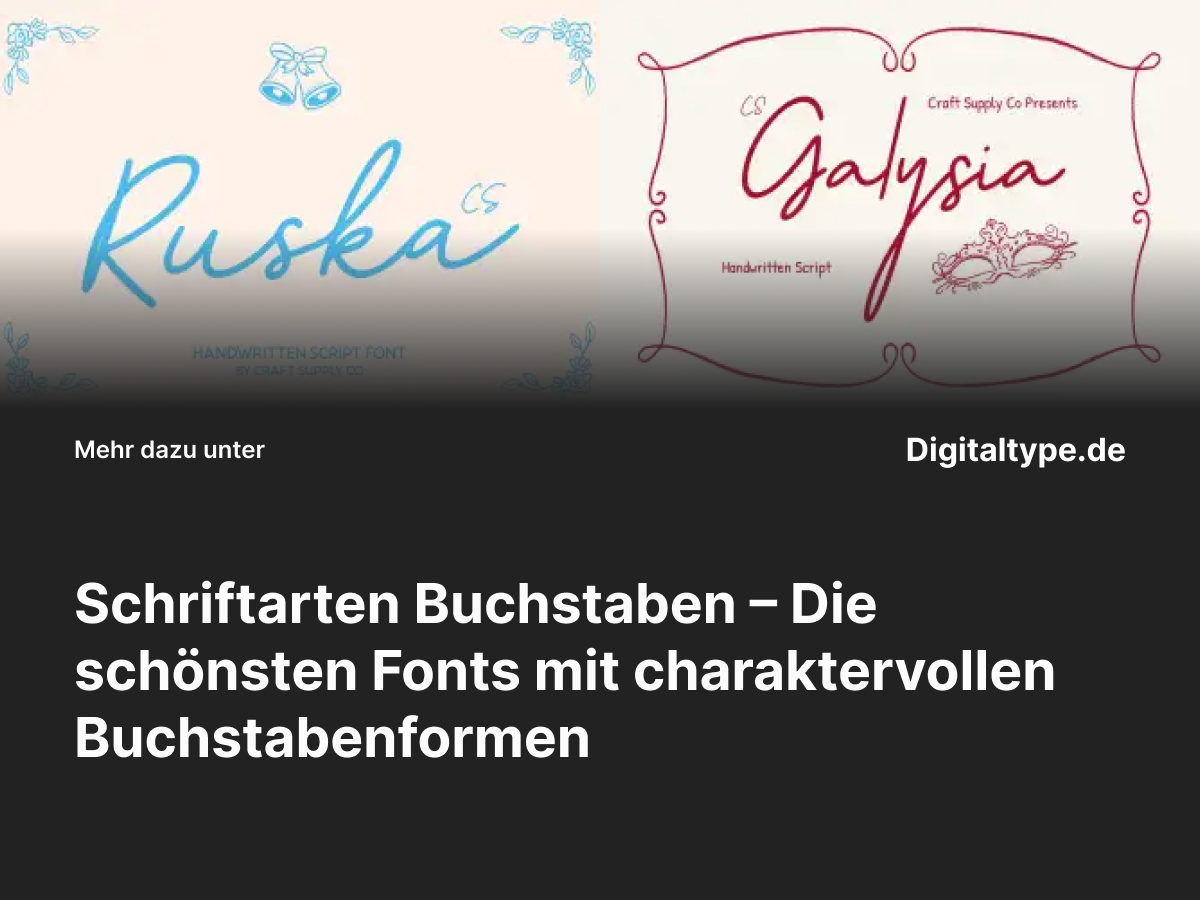
Buchstaben sind das Herz jeder Typografie – und die Wahl der richtigen Schriftart entscheidet darüber, ob dein Design elegant, verspielt oder modern wirkt. Besonders Schriftarten mit schönen Buchstaben sind heute gefragter denn je: Sie verleihen Logos, Einladungen oder Social-Media-Grafiken eine individuelle Handschrift und machen Texte zu visuellen Highlights. In diesem Artikel zeigen wir dir, worauf du bei der Auswahl achten solltest und welche sechs handverlesenen Fonts du unbedingt ausprobieren solltest.
Was macht eine Schriftart mit schönen Buchstaben aus?
Schöne Buchstaben erkennt man an ihren harmonischen Formen, rhythmischen Linien und ausbalancierten Proportionen. Sie wirken nicht nur dekorativ, sondern auch lesbar und ausdrucksstark. Je nach Stilrichtung kann eine Schrift elegant, künstlerisch oder modern wirken – von kalligrafisch bis minimalistisch.
Schriftarten Buchstaben mit Handwriting-Charakter sind besonders beliebt, weil sie Emotion und Persönlichkeit transportieren. Jede Linie erzählt eine kleine Geschichte, jeder Buchstabe wirkt individuell – fast so, als wäre er von Hand geschrieben.
Wann du Schriftarten mit besonderen Buchstaben verwenden solltest
- ✔️ Für Logos, Branding und Verpackungen mit persönlicher Note.
- ✔️ In Hochzeitseinladungen, Postkarten oder Zitat-Designs.
- ✔️ Für Social-Media-Grafiken, um Emotion und Stil zu zeigen.
- ✔️ In kreativen Projekten, bei denen Handarbeit und Individualität im Vordergrund stehen.
Eine Schriftart mit schönen Buchstaben kann deinem Design Authentizität verleihen – ideal für Marken, die Nähe und Persönlichkeit ausstrahlen wollen.
Die 6 besten Schriftarten mit schönen Buchstaben
Hier findest du sechs ästhetisch gestaltete Schriftalternativen mit wunderschönen Buchstabenformen – von feinen Monoline-Linien bis hin zu schwungvollen Script-Schriften. Jede dieser Fonts ist perfekt für kreative und emotionale Projekte geeignet.
1. CS Ruska Handwritten Script Font
CS Ruska ist eine handgeschriebene Script-Schrift mit fließenden, eleganten Buchstaben. Sie kombiniert Natürlichkeit und Raffinesse und eignet sich perfekt für Branding, Zitate oder Einladungen. Die feinen Linien verleihen jedem Design eine persönliche, charmante Note.
2. CS Galysia Handwritten Script Font
CS Galysia überzeugt durch einen modernen Schreibstil mit geschwungenen, harmonischen Buchstaben. Diese Schriftart ist ideal für feminine Marken, Lifestyle-Projekte und dekorative Anwendungen, bei denen Ästhetik im Vordergrund steht.
3. CS Elysia Monoline Script Font
Elysia bietet elegante, gleichmäßige Linien, die jedem Buchstaben eine klare und minimalistische Form geben. Diese Schriftart Buchstaben eignet sich perfekt für Signaturen, Social-Media-Designs oder dezente Branding-Projekte mit edlem Charakter.
4. CS Brisa Monoline Script Font
CS Brisa kombiniert einfache Linien mit einem natürlichen Schreibfluss. Sie wirkt ruhig, freundlich und modern zugleich – perfekt für kreative Designs, die auf Authentizität setzen. Besonders gut geeignet für Branding, Verpackungen oder kreative Blog-Grafiken.
5. CS Belluga Handwritten Whimsy Font
CS Belluga bringt verspielte Energie ins Design. Die schwungvollen, handgezeichneten Buchstaben verleihen jedem Projekt Dynamik und Lebensfreude. Ideal für kreative Layouts, Lifestyle-Designs oder Kinder- und Eventmarken.
6. CS Ringo Handwritten Script Font
CS Ringo ist eine moderne, leicht kantige Handschrift mit originellen Buchstabenformen. Sie vermittelt Selbstbewusstsein und Individualität – ideal für moderne Marken, Social-Media-Designs oder visuelle Statements mit Charakter.
Design-Tipps für Schriftarten mit schönen Buchstaben
- 1. Setze Akzente: Nutze schöne Buchstaben-Schriften für Headlines oder Zitate, um Aufmerksamkeit zu erzeugen.
- 2. Kombiniere mit Sans-Serif: Eine klare Begleitschrift sorgt für Lesbarkeit und Balance.
- 3. Achte auf Raum: Lass handgeschriebenen Fonts genug Platz zum Atmen – zu enge Zeilen wirken unruhig.
- 4. Wähle Farben mit Bedacht: Weiche, warme Töne wie Beige, Rosa oder Creme harmonieren perfekt mit Script-Fonts.
Fazit: Schriftarten mit schönen Buchstaben für kreative Designs
Schöne Buchstaben-Schriftarten bringen Eleganz, Persönlichkeit und Emotion in jedes Projekt. Ob du ein Logo gestaltest, ein Zitat designst oder deine Marke emotional auflädst – die richtige Schrift kann wahre Wunder bewirken.
Die oben vorgestellten Fonts sind ideal für Designer, die Ästhetik und Individualität kombinieren möchten. Probiere sie aus und finde heraus, welche Schriftart am besten zu deinem Stil und deiner Botschaft passt.